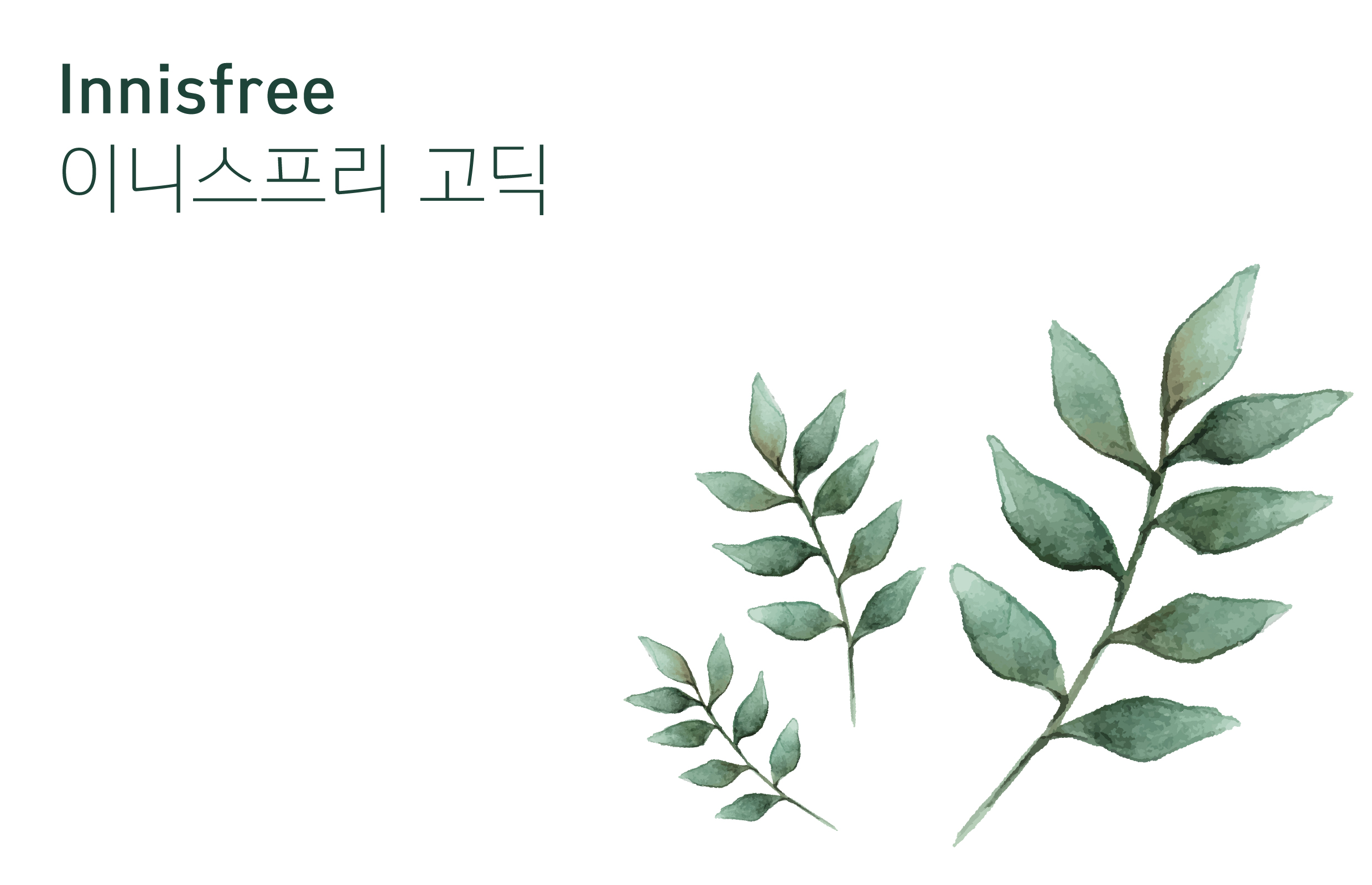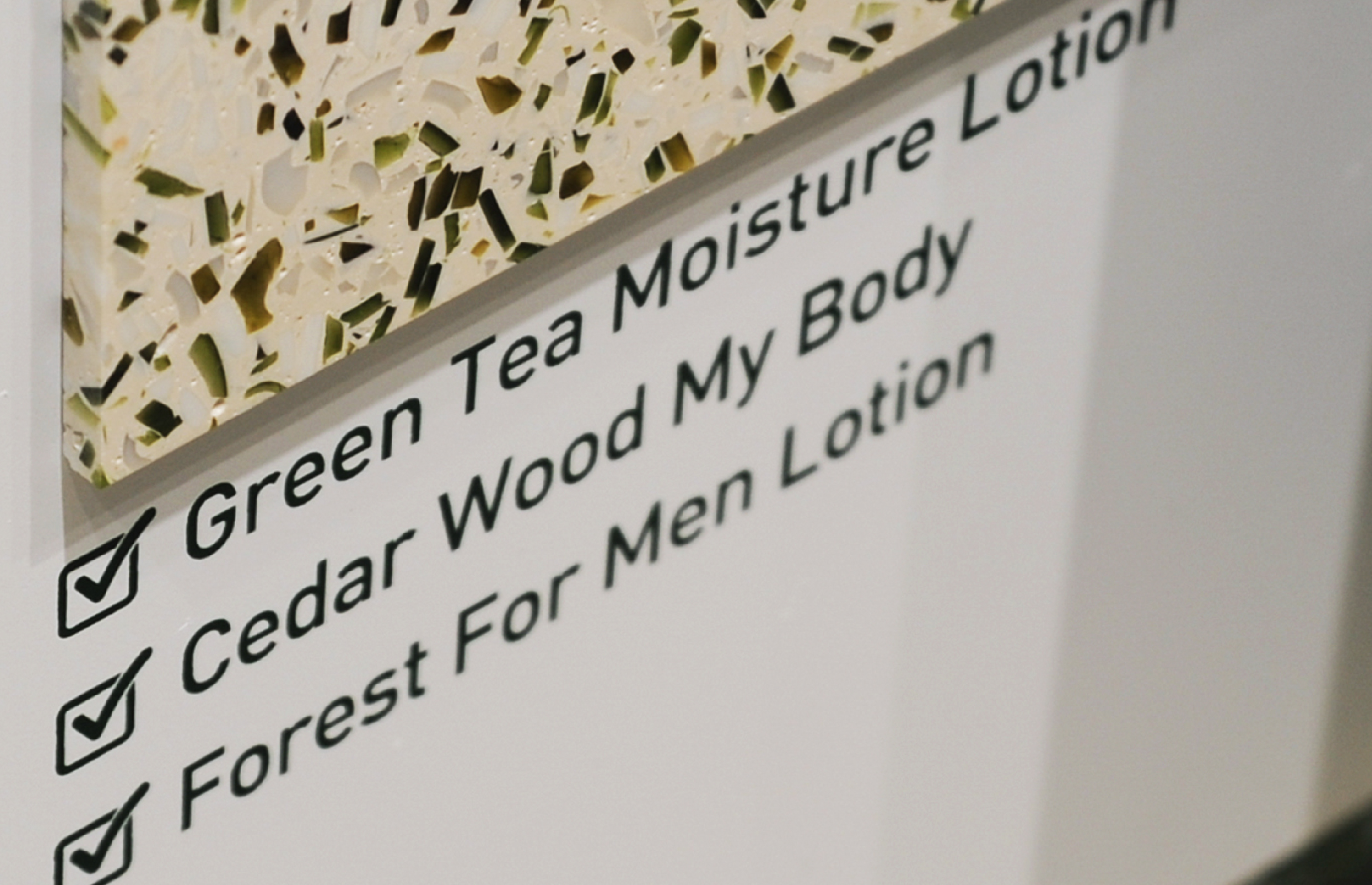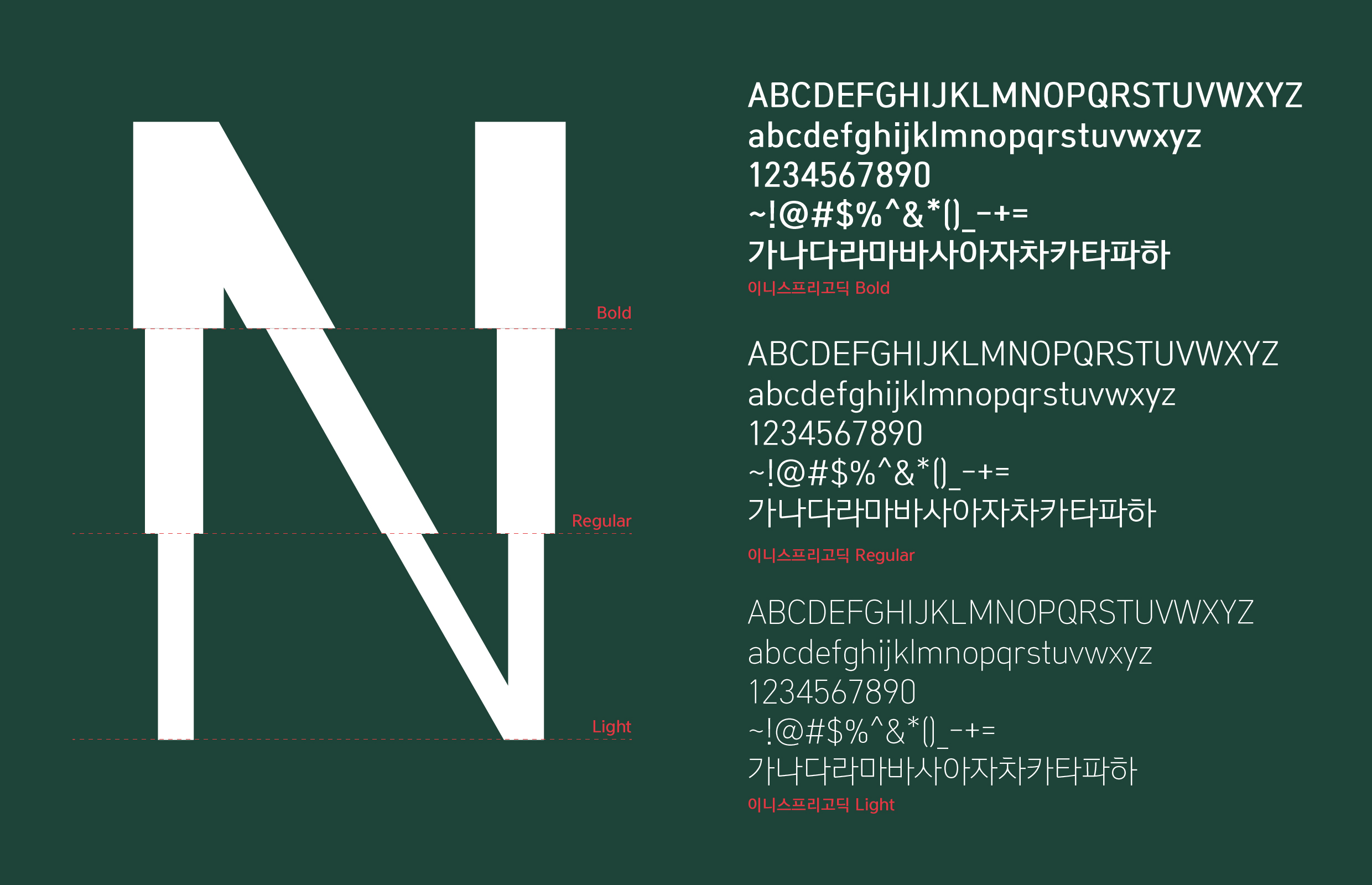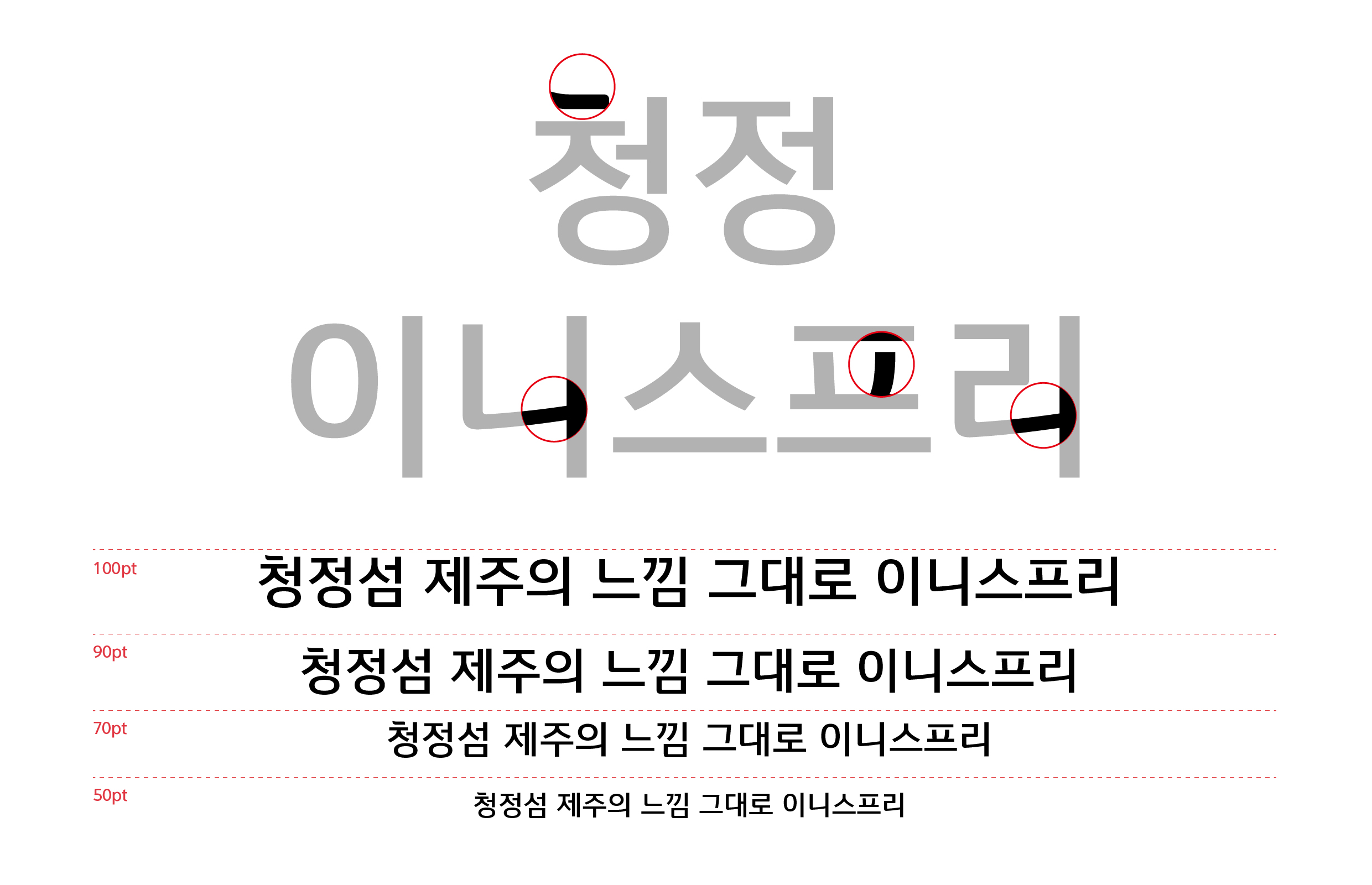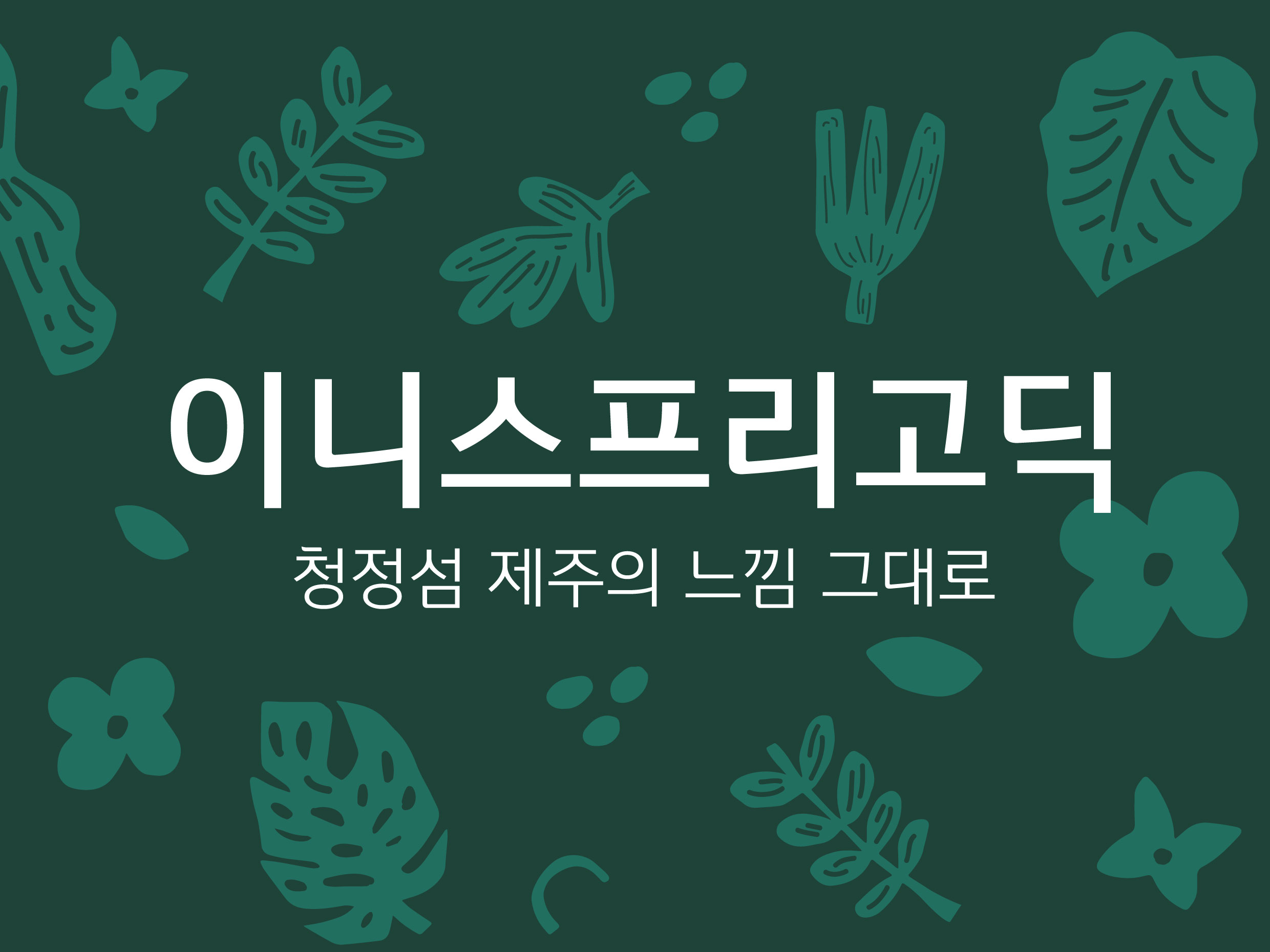
아모레퍼시픽 [이니스프리고딕]
기 개발된 ‘이니스프리 IF퓨어고딕’의 리뉴얼 디자인으로 시작. 퓨어고딕의 아이덴티티를 반영하면서 본문에서의 쓰임을 강화한 것이 특징이다. 친환경 그린 라이프를 실천하는 자연주의 브랜드 이니스프리의 깨끗한 자연과 건강한 아름다움을 담아냈다.
아모레퍼시픽